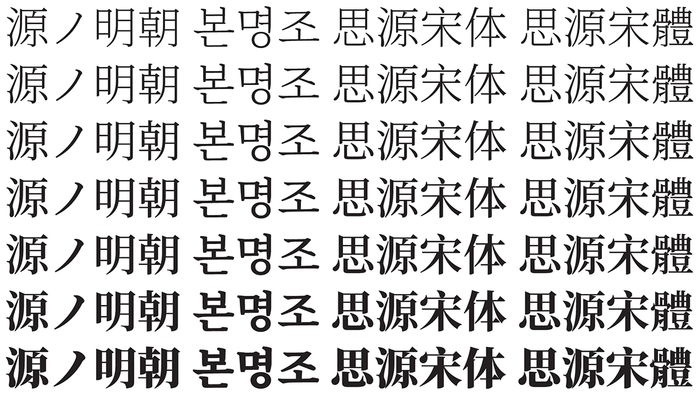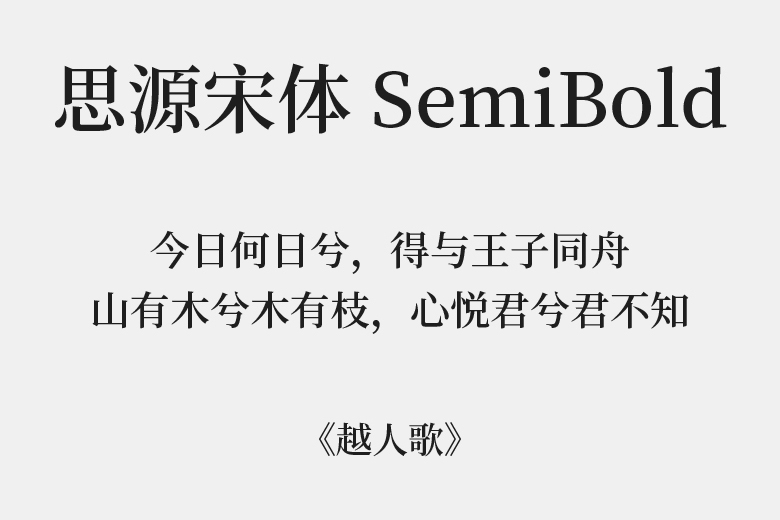
谷歌携手Adobe推出超好看的的思源宋体(可商用)免费下载使用
Google 和 Adobe 再宣布推出思源宋体 (英语:Source Han Serif)免费字型下载!(或称思源明体,谷歌将中国大陆简体中文命名为宋体,香港、澳门及台湾则是明体;Adobe 没有分别一律称为思源宋体),这也是让许多用户期待以久的字型,有别于黑体的显示效果,其实思源宋体在细节处理上更接近中文感觉。